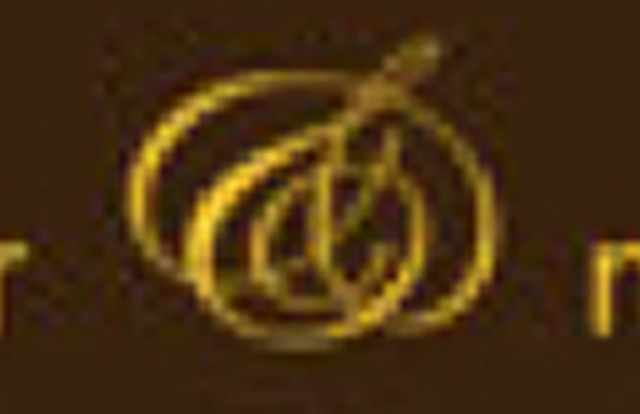
Ich suche ein, ich vemute " &" Zeichen
Guten Tag, auf der Suche nach einem Zeichen das "&" ,siehe Foto, bin ich in diese Community gekommen.
In Zapfino gibt es ein Ähnliches, jedoch nicht genau dieses. Bin gespannt ob wir es herausbekommen.
Das Zeichen wird leider nicht dargestellt, drum als Screenshot: